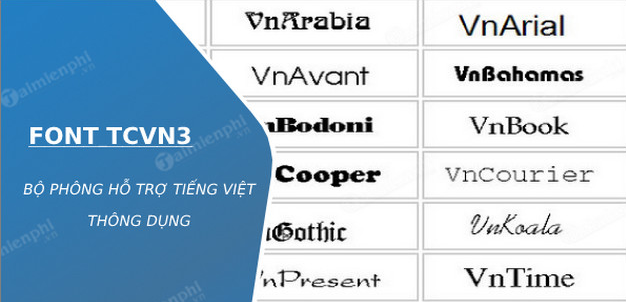
Bộ Font: Font TCVN3
Phân loại: Đa dạng màu sắc
Font TCVN3 là bộ font thuộc bộ font chữ việt hóa . Font TCVN3 là một chuẩn mã hóa ký tự tiếng Việt cũ, thường được sử dụng trên các máy tính và phần mềm trong thập kỷ 90. Hiện nay, khi các chuẩn Unicode đã trở nên phổ biến, nhu cầu chuyển đổi và sử dụng tài liệu từ font TCVN3 sang các định dạng hiện đại như Unicode vẫn còn rất nhiều. Việc hiểu và biết cách xử lý font TCVN3 sẽ giúp bạn dễ dàng làm việc với các tài liệu cũ, đảm bảo tính tương thích và duy trì được toàn bộ nội dung văn bản gốc mà không gặp lỗi hiển thị.